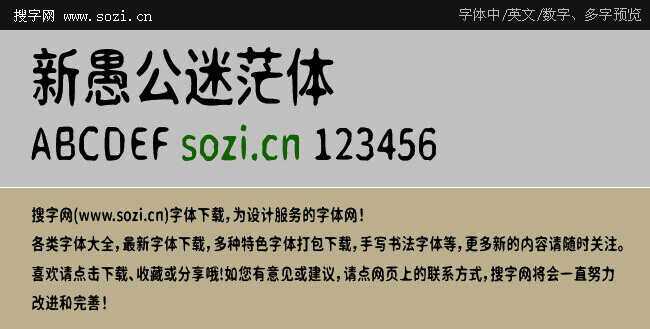
新愚公迷茫體
搜字網(wǎng)提供一款新愚公迷茫體中文藝術(shù)字體下載,新愚公迷茫體是對(duì)思源黑體進(jìn)行改造的一款字體。這款字體加入了大幅度隨機(jī)的扭曲效果,讓字體看去上就好像開始要融化了一樣的感覺。適合圖書設(shè)計(jì)、包裝設(shè)計(jì)、海報(bào)設(shè)計(jì)等應(yīng)用。